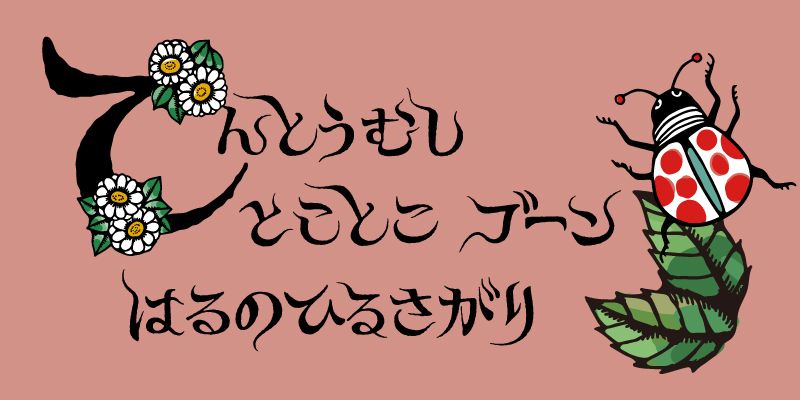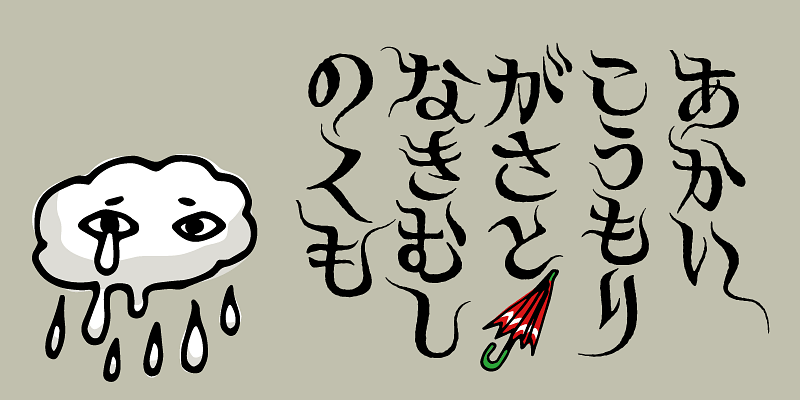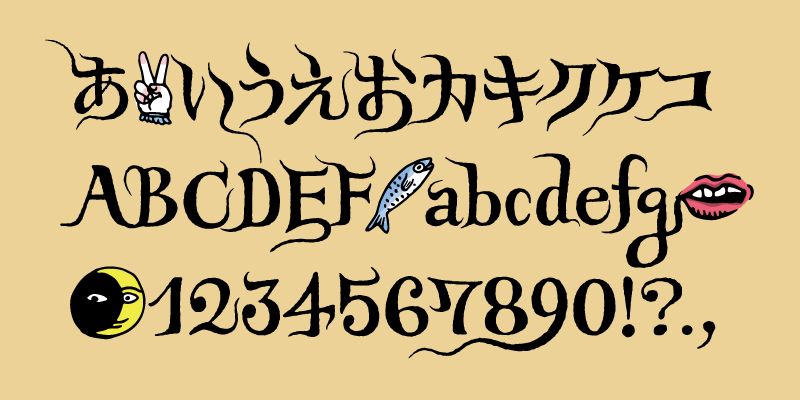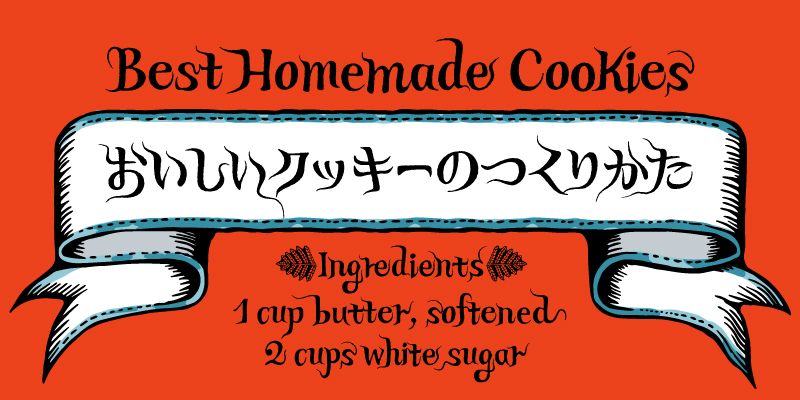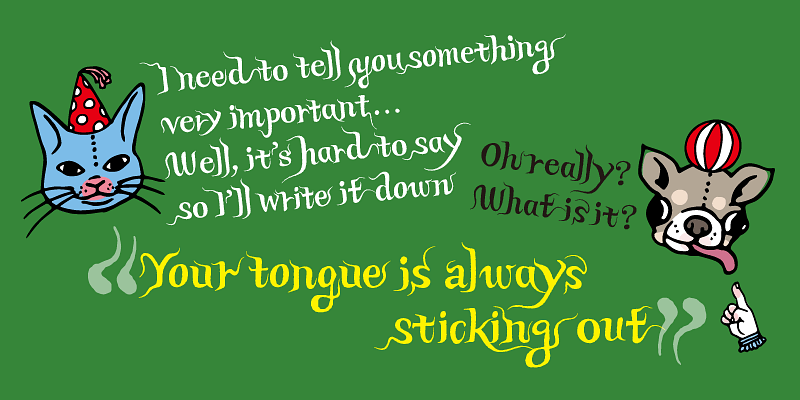
Higumin est une police de caractères Adobe Originals conçue par Ryoko Nishizuka. Celle-ci se base sur les lettres manuscrites et les illustrations de l’artiste et peintre Yuko Higuchi. La police contient des caractères originaux et caractéristiques, ainsi qu’une grande variété d’émoticônes colorées. (Higumin est une police de sous-ensemble qui n’inclut pas les caractères kanji/idéographiques).
Cette police de caractères est parfaite à des fins d’affichage, y compris pour la publicité, les titres et les en-têtes de livres, etc.
Higumin contient également de nombreux glyphes alternatifs sélectionnés automatiquement à l’aide de la fonction OpenType Contextual Alternates (« calt »). Ces alternatives amplifient le style manuscrit de la conception de la police.
Le programme Adobe Originals a débuté en 1989 en tant que fonderie typographique interne chez Adobe, réunie pour créer des polices originales d’une qualité de conception, d’une fidélité technique et d’une longévité esthétique exemplaires.
Aujourd’hui, la mission de l’équipe Type est de créer des polices sophistiquées, voire expérimentales, qui explorent les possibilités du design et de la technologie. Les polices publiées sous le nom d’Adobe Originals sont le résultat d’années de travail et d’études, et sont considérées comme les normes de l’industrie pour l’ambition et la qualité de leur développement.